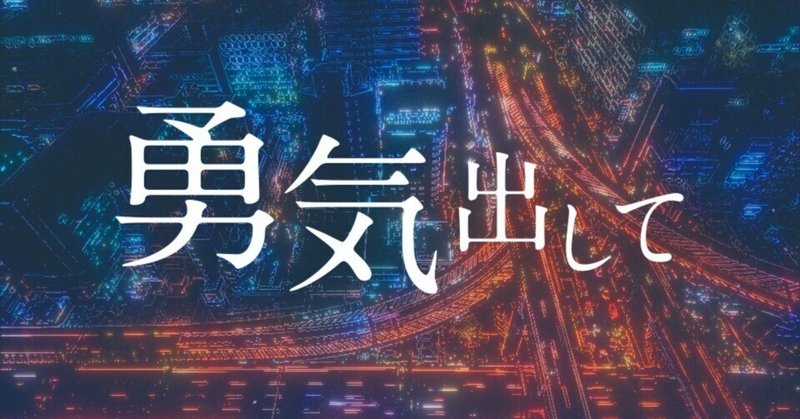
私のフォント使いこなし術 第3回 成田雄輝「アーティストが繊細に組み立てた言葉を、シンプルに伝わりやすく見せたい」
第3回は、GReeeeNやクアイフなどのリリックビデオを手がける映像作家の成田雄輝さんに伺います。
成田雄輝 Yuki Narita
映像作家/モーショングラフィックデザイナー
北海道出身。独学で映像を学び、2019年よりフリーランスとして活動。モーショングラフィックス、VFXなどを得意とし、MV・LV・WebCMなどを中心に制作する。
1 リリックビデオという映像ジャンル
現在、リリックビデオの制作を中心に活躍する成田さんですが、最初から映像作家を志望していたわけではありませんでした。
「もともとは、10代の頃に自分でやっていたバンドのプロモーション活動のために、映像やCGの勉強を始めたんです。AdobeのAfter EffectsやPremiere、Illustrator、Photoshopなどのアプリは、動画サイトを見ながら独学で覚えました。
自分がバンド活動をやめてからも映像の依頼をいただくことが多かったので、3年ほど前から映像作家の活動に力を入れるようになったんです。独学で始めていても、ミュージックビデオの世界は表現が自由で、映像の内容が良ければ評価されるのであまり問題はなかったんですが、業界用語はまったく知らなかったので、例えば『ザブトン(文字を読みやすくするために背景に敷く四角や丸の下地)入れといて』って言われても『なんだそれ?』ってわからなくてググったり。そういう苦労はありました」
リリックビデオはミュージックビデオの一種で、曲に合わせて歌詞を表示した映像です。日本では動画サイトなどで顔出しNGの歌い手やボカロP(ボーカロイド=音声合成技術による歌を使って曲を作る人)が、表現手法のひとつとして取り入れたのをきっかけに、3年ほど前から作られる数が増えてきています。
「リリックビデオの制作は基本的に音楽が先にあって、そこに映像をつけていきます。自分の場合は、映像にCGなどの加工を加える手法が多いんですが、それだけではなくまずは曲をしっかり理解した上で、そこに合う映像をアーティストさんやレーベルの方たちと話し合いながら一緒に完成を目指していくという仕事ですね」
成田さんはこれまでにGReeeeNのリリックビデオ3本を含め、多数のメジャーアーティストの作品を手掛けています。リリックビデオという新しい表現のジャンルだけに、どのように依頼が来るのか、といったことも気になるところです。
2 シンプルで伝わりやすいフォントを選ぶ
リリックビデオが流行する背景を、成田さんはこう分析します。
「時代とともに歌詞が複雑な曲が多くなっているので、言葉の裏側や、繊細な組み立てを理解したり、自分を重ねて曲を聞いたりするときに、リリックビデオの方が心に響きやすいんじゃないかなと思っています」
そんな歌詞の表現には、背景の映像や表示するタイミング、モーションのかけ方などのテクニックより前に、ベースとなるフォントの選択が重要です。
「アーティストさんやレーベルの方もフォントにこだわる方が多いです。制作の前段階からフォントへの要望をいただくこともありますし、こちらの制作の中でも何回もフォントを入れ替えてみたりと、一発で決まることはありません。僕の場合はシンプルで伝わりやすいのが好きで、アーティストさんの曲がどう伝わるかが大切だと思ってます。自分が『こうしたい』っていうよりも、ここはシンプルに歌っているからシンプルなものが合うよな、というふうに、常に伝わりやすさを意識してます」
フォントには数多くの種類がありますが、成田さんはフォントの成り立ちや歴史、これまで使われてきた用途といったものにはあまり興味がなく、先入観をあまりもたない状態で実際に歌詞に当ててみて選ぶことが多いのだそう。
「やっぱり曲ありきでフォントを探すので、これが使いたいといったこだわりみたいなものはありません。フォントを知りたいと思って知るというより、ひたすら合うフォントを探す中で『ああこういうフォントがあるんだ』という経験がどんどん溜まっていくって感じですね。MORISAWA PASSPORTは、フォントの選択肢がめちゃめちゃあるってことと、1つ1つのフォントのクオリティが高いところが魅力です。それ以外のフリーフォントもインストールしているんですが、ほとんど使ってないですね。なんか微妙に違うというか、妥協するようなところがあって。モリサワのフォントだとハマる感覚があるというか、『なんか違う』『なんか惜しい』みたいなところを解決してくれることが多いですね」
使用フォント:リュウミン
REEKの『Word』では、日本語のラップに合わせて文字が文節ごとに浮かんだり、迫ってきたりしたかと思うと、単語ごとに打ち付けるような動きの表現や、1文字ごとに切り替わる、文字によってはパーツに分解されるような表現までもが盛り込まれています。成田さんならではの文字の使い方、フォント選びの特徴のようなものはあるのでしょうか。
「けっこう僕の作品ってすごいバラバラなんですよ。アーティストさんによって全然違っていて、それが僕の特徴というか、大切にしていることなんですけど。お決まりの手法っていうのはなくて、曲によって全然違うことをやってみたりとか、コテっとしたのもあればさっぱりしたのもあればって感じで変えてます」
3 曲の中でのフォントの切り替え方
成田さんのリリックビデオでは、曲の展開や歌詞の内容によって細かくフォントを切り替えて使用しています。今回紹介してもらった『アカリ』のリリックビデオも、カラフルな夜景の映像にやさしく繊細に浮かび上がるリュウミンの歌詞から始まり、パワフルな歌い方に合わせて跳ねるようなゴシック体、そしてラップ部分では歌詞が心に突き刺さるようなA1明朝が曲調とともに気持ち良く切り替わっています。
使用フォント:A1明朝/リュウミン
またフォント選びだけでなく、スタイリッシュに見せたい時は文字間を開けたり、逆に文字間を極端に詰めたり斜体をかけたりすることで印象を強めるなど、組み方やモーションでの表現にも使い分けが見られます。
「文字の使い方に関しては、他の方が作っているリリックビデオから学ぶところは多く、実際にその表現を取り入れてみることもあります。ただ、自分のやりたいことや、かっこいいと思うことは大切だとは思うんですが、それよりもアーティストさんの属性を見極めて一緒に作り上げていくことの方が優先です。1つの画面に出てくる文節ごとにやるわけではなく、あまり変えすぎてもごちゃごちゃしてしまうので、Aメロは明朝体とこのモーションでいこうとか、そういうふうに決めています」
成田さんが使用されるフォントはほとんどが明朝体で、曲の中でアクセントとしてゴシック体が使われることがあっても、ごく一部に限られている印象です。
「ゴシック体で作るのがうまい方はすごいかっこいいものを作るんですが、単純に僕の制作するものがあまりゴシック体向きじゃないということもあります。例えばアイドル系の曲とか、可愛いゴシックでさまになったりするんですけど、あんまり自分にはそういう依頼がなくて。ロックバンドとか、メッセージ性を大切にするような音楽が多いので、基本的に明朝体なんです。デザインの仕方というかモーションを動かしていく中でも、ゴシック体は使い方が難しいなと思います。それでもアクセント的な使い方をしたいときや『今回ゴシック体でお願いします』って言われることもあって、そんなときは見出ゴMB31やUD新ゴを選んでいます」
4 明朝体の表情による使い分け
成田さんは、そのほかにもよく使うフォントとして、リュウミン、見出ゴMB31、太ミンA101、A1明朝の4書体を上げてくれました。中でも特にリュウミンへの信頼度は群を抜いているそうです。
「リュウミンがめちゃめちゃ好きで愛用しています。クセがなくて表現しやすく、縦横の比率を変えたり、傾きを変えたりするだけで全然違うフォントにも感じられます。シンプルでクセがないデザインが日本語の美しさだと思っているので、常にリュウミンに行きがちなんですけど、力強く歌っているところには細いリュウミンよりもA1明朝が合うなとか。A1明朝には湿度感、情感のあるフォントという印象があるので、それを文字ごとに大きさを変えたりして使うことが多いですね。文字が動いてモーションが動いてハマったときに、ベタっとした感じがあると、そこで力強さを感じたりします。そういう強弱で明朝を使い分けています」
使用フォント:リュウミン
クアイフの『ナンバーワン』でも、リュウミンが多用されています。曲や歌い回しの繊細さと、リュウミンの書体や文字の輪郭、モーションが気持ちよくハマっています。動きの中で文字がキュッと全体に詰まって組まれたり、逆に開放的に広がっていくような場面もあり、リュウミンのやや繊細な表情がよく活かされているように感じられます。
「日本語の配置ってすごく難しいな、っていつも思っています。リュウミンは文字間をめちゃめちゃ詰めて使うことも多いんですが、スタイリッシュさを出したいときは字間を開けて一文字一文字を見せたり、繊細な曲だと文字と文字とを離したり。もちろん歌っているテンポや歌い回しによります。曲に抑揚をつけてるところは、文字も抑揚をつけて表現しようとしてます」
5 日本語でもスタイリッシュに
成田さんが音楽に興味を持ち始めた10代の頃には、すでに洋楽で数多くのリリックビデオが作られていました。しかし、その頃の成田さんは、日本語では洋楽のようなシンプルさやスタイリッシュな感じは出せないと感じていたそうです。その考えが変わったのはモリサワフォント、特にリュウミンとの出会いでした。
「リュウミンを見つけたときに、これはすごいなって思いました。クライアントの方にも『ハマってる』って言われることが多いフォントです」
今後の表現の仕方や、作っていきたいものは特にないという成田さん。曲次第、依頼次第でさまざまな表現を続けていきたいと語ってくれました。日本ではボカロの文化から広がったこともあり、少しマイナーな印象もあったリリックビデオですが、成田さんはこのポジションが変わっていく可能性を示してくれます。
「日本語でも、もっとスタイリッシュで伝わりやすく、シンプルでかっこいいリリックビデオを作りたいっていうのが、僕がもともと持っていたテーマです。海外のものに影響を受けつつ日本語で進化したような作品を目指しています。なので日本でもメジャーなアーティストさんや、スケール感が大きな人とも、どんどん仕事をしていきたいですね」
6 「気になる」フォント
UD新ゴ コンデンス70
「UD新ゴのカクカクした形が好きです。リリックビデオにはどうしても明朝体が多くなってしまうんですが、ゴシック体も使ってみたいとは思っています。コンデンス書体を使ってサイバーな感じの表現とか、新しいテイストのリリックビデオも面白んじゃないかと。看板のような表現とか、ちょっと色収差入れてみたり、ノイズと合わせると未来感あって面白い表現ができそうな気がします」
ぺんぱる
「やさしさや温もり感のある手書きのフォントはいつも探していて、フリーフォントもよく見るようにしているんですが、少しのテイストの違いで雰囲気もガラッと変わってしまうので、選択肢は多いほど嬉しいです。「ぺんぱる」はまだ使ったことがないのですが、質のいい手書きフォントということで、書体をセレクトするときに試してみたい候補のひとつです」